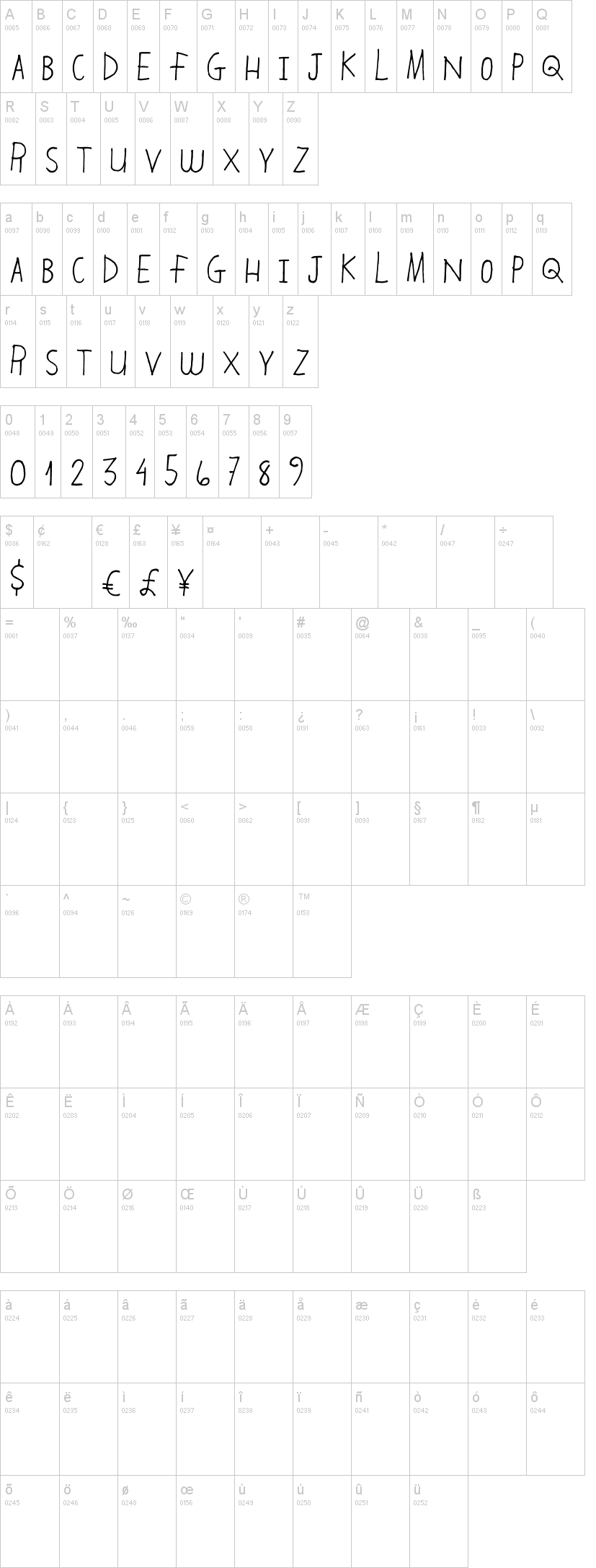
Handing Over
Handing Over 字体是一款清新的手写字体,由荷兰设计师 Peter Verheul 创作。它有着温暖的气息,可以很好地表达出情感,是一款非常适合用于报纸、海报、书籍封面等设计中的字体。它的字形设计灵活,可以根据需要调整字体的大小,从而使得字体可以被有效地应用到不同的设计中。
Handing Over是一款非常不错的手写艺术字体,具有很好的视觉感,适合于文化类的宣传设计、商业类品牌的广告和产品包装设计以及个性化文字排版等较多场景。